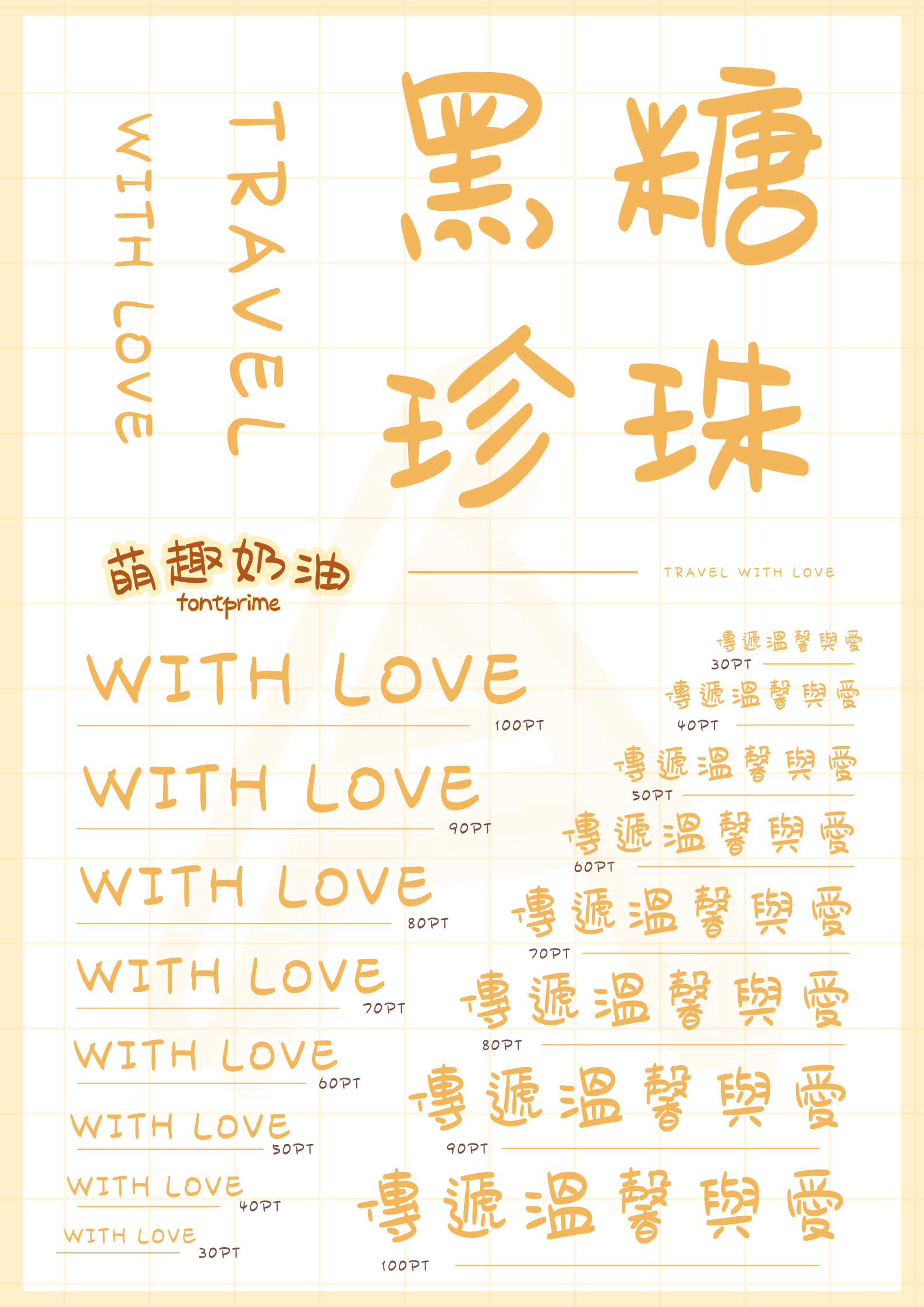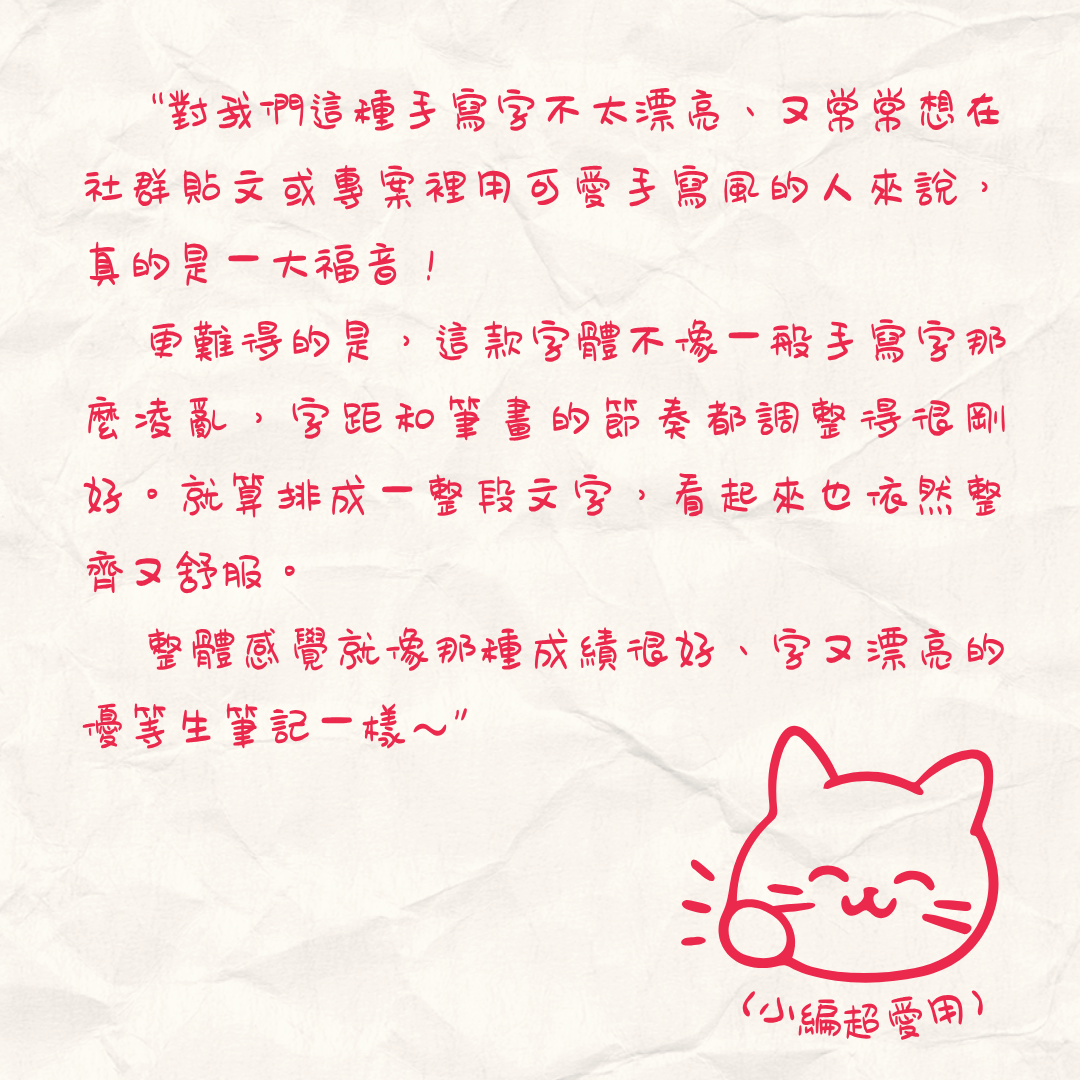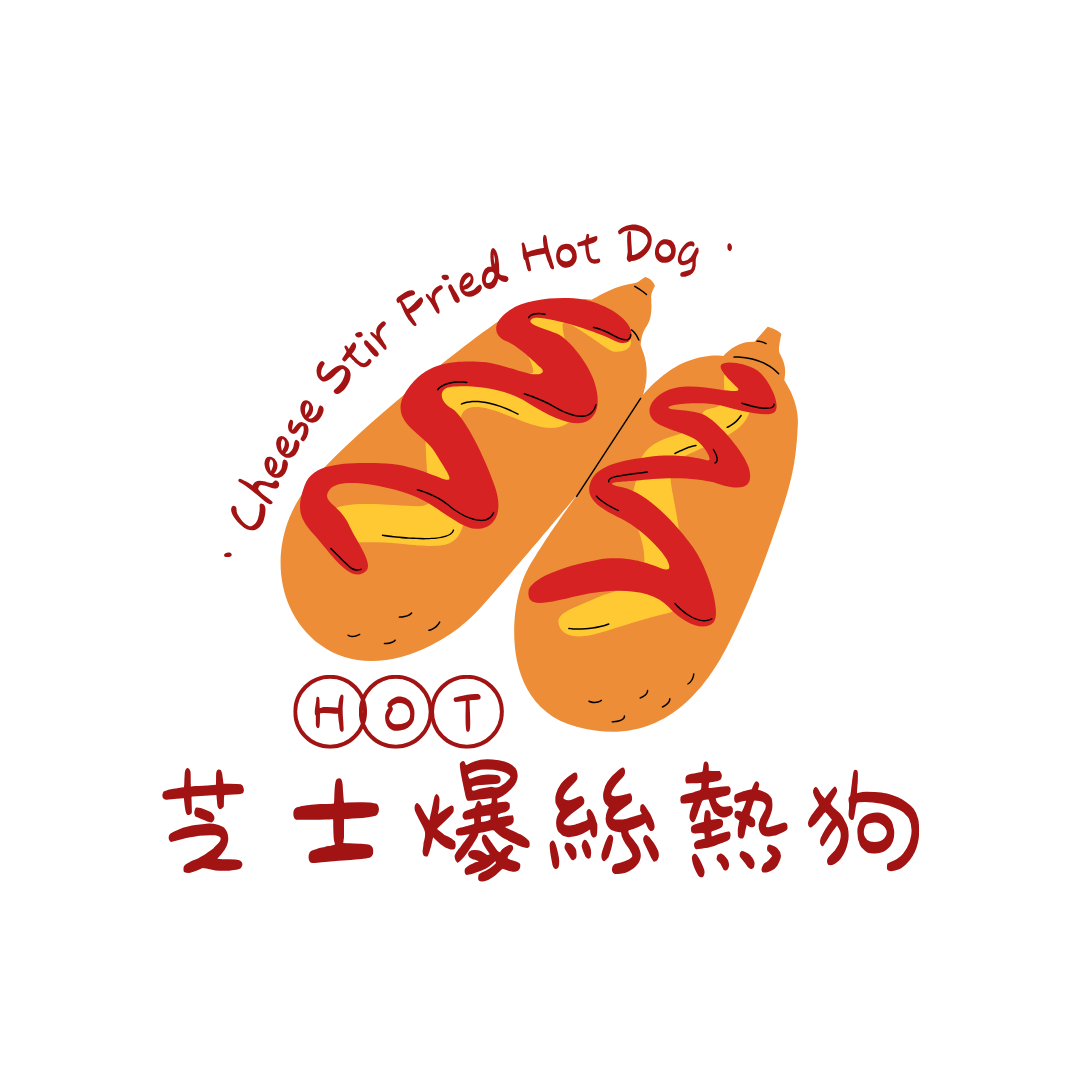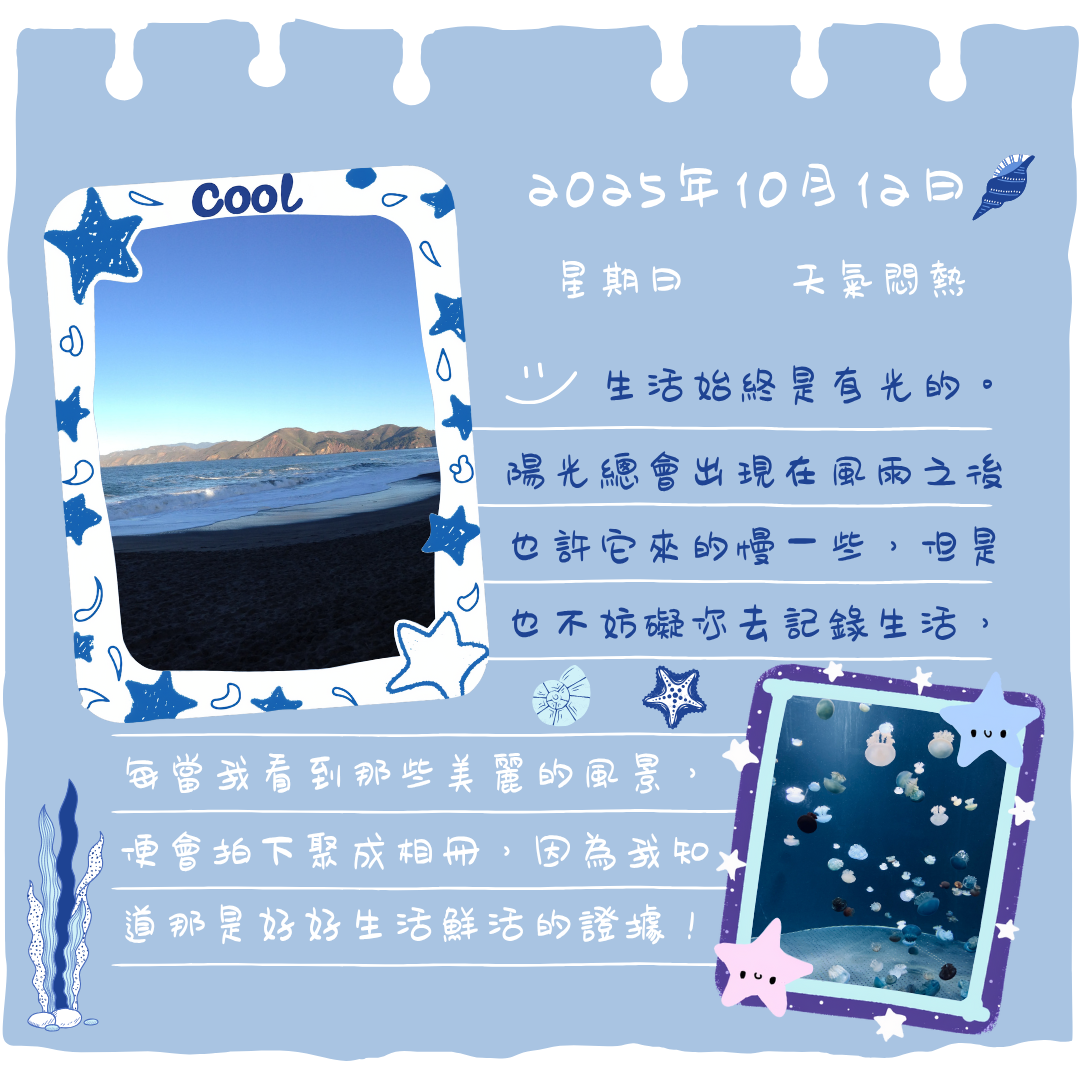
字嶼萌趣奶油體
字嶼萌趣奶油體:唤醒视觉的童趣魔法字体
身為設計師的你,是不是常陷入「字體選購困境」?想做一張親子活動廣告,翻遍字庫都是冰冷的機械體,沒有半分童真溫度;為甜點店設計菜單,想找款手寫感繁體字,要麼筆畫生硬,要麼轉換後出現錯字;趕影視傳媒的兒童節目海報,卡通字要麼太誇張顯雜亂,要麼不支持繁體 —— 其實,你缺的不是設計靈感,而是一款「懂設計場景、有溫度又實用」的字體:字嶼萌趣奶油體。
覆蓋設計師常用場景,一款字體搞定多需求
- 廣告設計:不論是孩童用品宣傳、親子遊樂園海報,還是可愛風日用品廣告,用它做標題能瞬間抓住視線;
- 影視傳媒:兒童動畫片尾字幕、親子節目 LOGO、活動宣傳短片的重點文字,用這款字體能自然融入畫面,不顯突兀。比如幼兒頻道的節目預告,字體與卡通畫面呼應,家長和孩子都能感受到溫度;
- 店鋪設計:甜點店招牌、親子餐廳菜單、玩具店價目牌 —— 手寫感的奶油體能拉近與顧客的距離,比如餅乾店門頭用它做大字,路人忍不住駐足拍照,間接提升店鋪曝光;
- 美食餐飲:蛋糕包裝盒、飲料瓶貼、市集小吃攤海報,童真感能勾起消費欲。比如水果茶包裝用它印「今日現做」,比普通列印字更有「手工鮮製」的信任感。
標準字集:自由創作,靈活應用
字嶼萌趣奶油體 TC 以臺灣常用標準字集為標準,參考jf7000字集,包括注音符號、英文字母、阿拉伯數字和標點符號,約7640字以上。涵蓋了日常生活和設計中常用的漢字、字母、數字以及各類標點符號,支援大多數使用情境。
無論是面向大眾的設計作品,還是涉及到國際交流、英文元素的設計專案,字嶼萌趣奶油體 TC 都能提供支援。(目前字集先以臺灣常用標準字為基礎建置,後續會逐步規劃擴充在地化用字,期待未來能更完整地服務書寫需求。)在處理英文單詞或數字信息時,其字母和數字的設計與漢字相互呼應,保證了整體排版的和諧統一。讓設計師在創作過程中可以更加專注於發揮創意,靈活地運用這款字體打造出各種獨具匠心的作品。